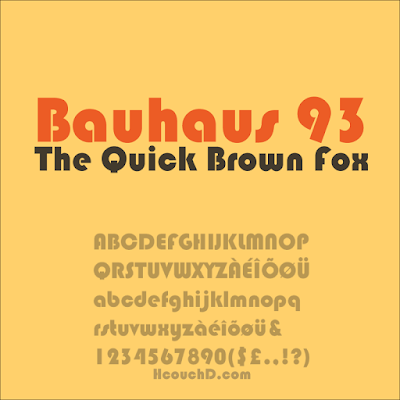
خط Bauhaus 93 خط جميل ، حيت أن له شكل مميز ، و سبق أن استعملناه في درس “ درس 41 : كيفية عمل تصميم سنة سعيد بإستعمال illustrator + ملف Vector ” ، يمكنك تحميل هذا خط من رابط أسفله …